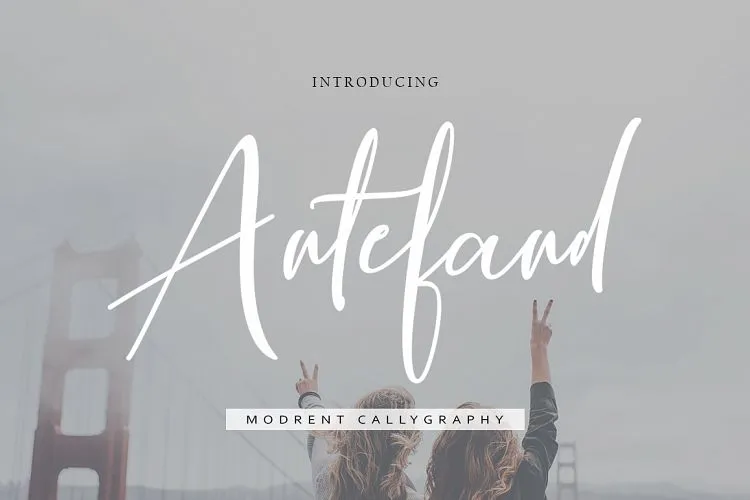
Nós apresentamos “Antefand Font”, especialmente pensado para você. Desenhada por mightype, Antefand Script é uma fonte de calligrafia moderna que reflete a atual tendência do estilo de escrita. Esta fonte é perfeitamente adequada para diversos usos, como marca, convites para casamentos, revistas, pratos de café da manhã, cartões de negócios, citações, flyers e muito mais. Se quiser experimentar antes de comprar esta fonte, ela é uma excelente opção.